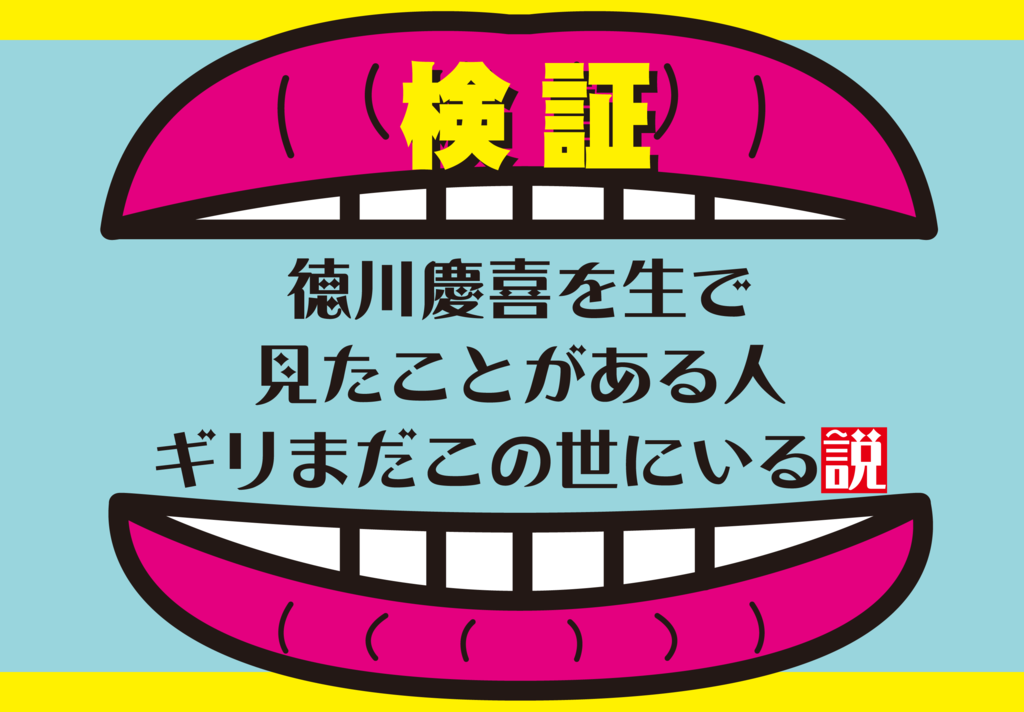
水曜日のダウンタウン
ダウンタウンの冠番組で芸能人が自らの提唱する様々な「説」をプレゼン、その「説」を検証した模様をVTRで紹介し、スタジオでパネラーとトークを行う。よくBPO(放送における言論・表現の自由を確保しつつ、視聴者の基本的人権を擁護するため、放送への苦情や放送倫理の問題に対応する、第三者の機関)に引っかかる事で話題になる(そういう企画の時こそ面白さが跳ねる)が、逆にギャラクシー賞(放送批評懇談会が日本の放送文化の質的な向上を願い、優秀番組・個人・団体を顕彰)を受賞したりもする番組。
水曜日のダウンタウンDVD第11巻おぼん・こぼんSPの特典、番組オリジナルおしぼりは投げてつかうもの説
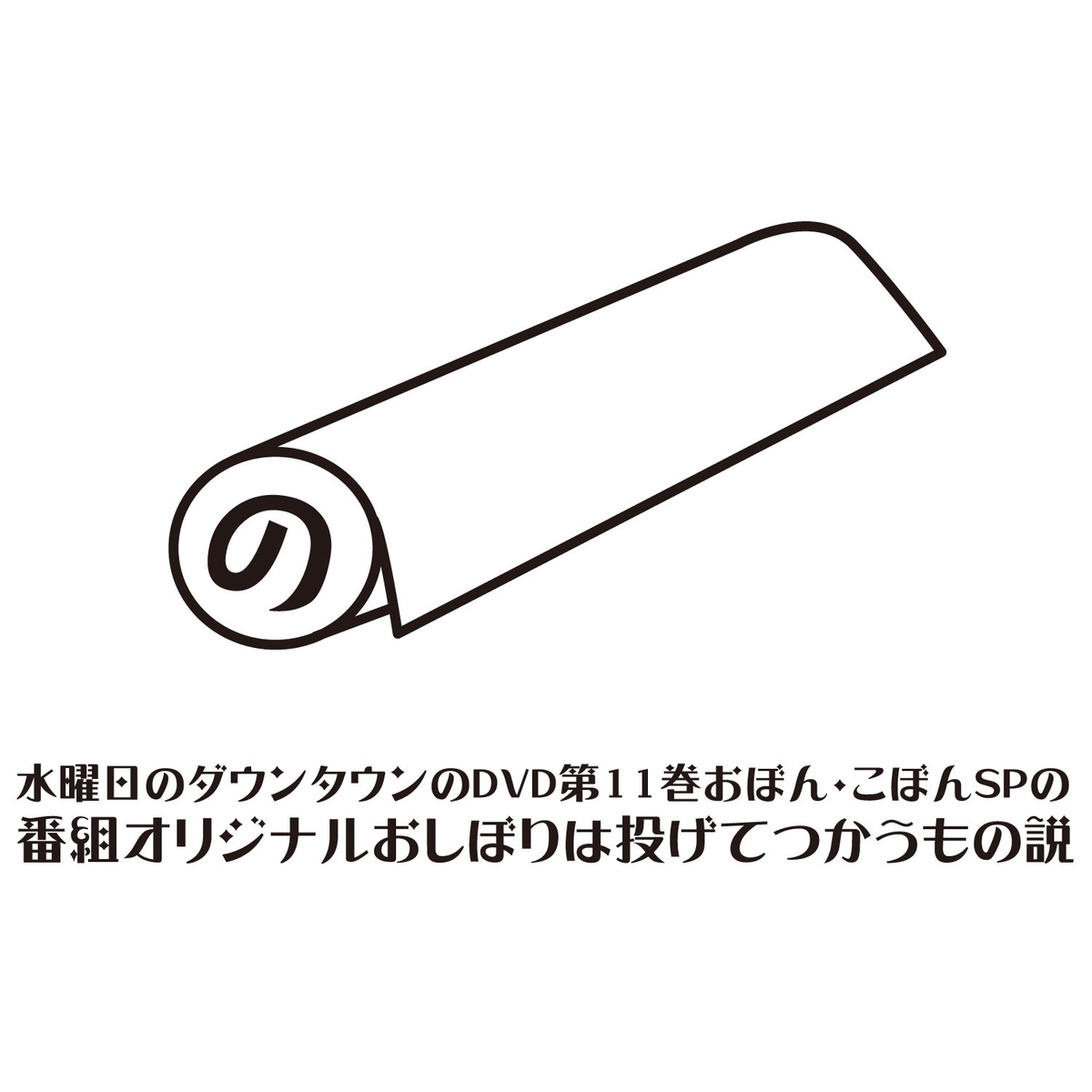
水曜日のダウンタウンDVD第11巻おぼん・こぼんSPの特典、番組オリジナルおしぼりは投げてつかうもの説で間違いないんでは。
73巻「ボーナス戦線異状なし!の巻」を検証した。番組常連の奇人バイきんぐ西村とナダルがくすぐられて吐いた内容により小峠が二度傷つけられた。
駄菓子がっちり食べまショー
79巻「駄菓子屋カルト王の巻を検証した。指定された金額分の駄菓子を食べる企画。あかつやアントニー、大トニーなどデブ芸人チームとフードファイターチームに分かれ商品の値段を伏せたまま先に10万円を食べたチームが勝利というルールだったが、思いのほか、金額がいかず、途中で駄菓子屋の閉店時間である19時までにどれだけ食べられるかにルールが変更した。